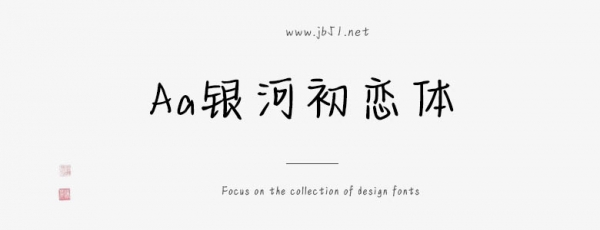
Aa銀河初戀體是一款不錯(cuò)的藝術(shù)字體,由Aa字庫(kù)出品,字體筆觸適中,字形端正,擁有字符數(shù) 8040和字形數(shù)8008,具有很好的視覺感,適合應(yīng)用于藝術(shù)設(shè)計(jì)、平面宣傳設(shè)計(jì)、網(wǎng)頁(yè)設(shè)計(jì),書法字帖等領(lǐng)域,需要的朋友可以前來(lái)本站下載。